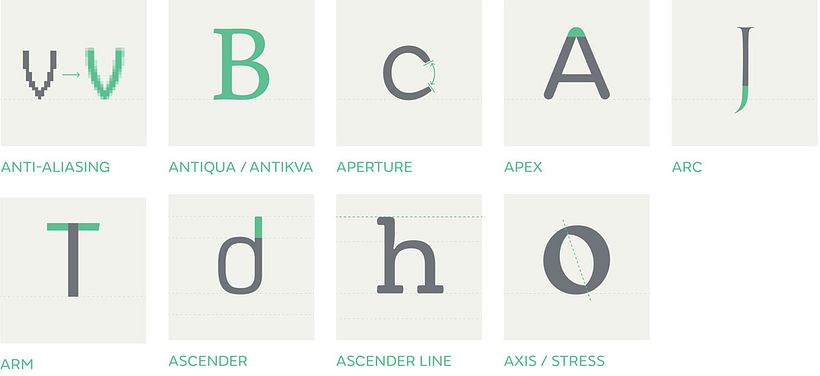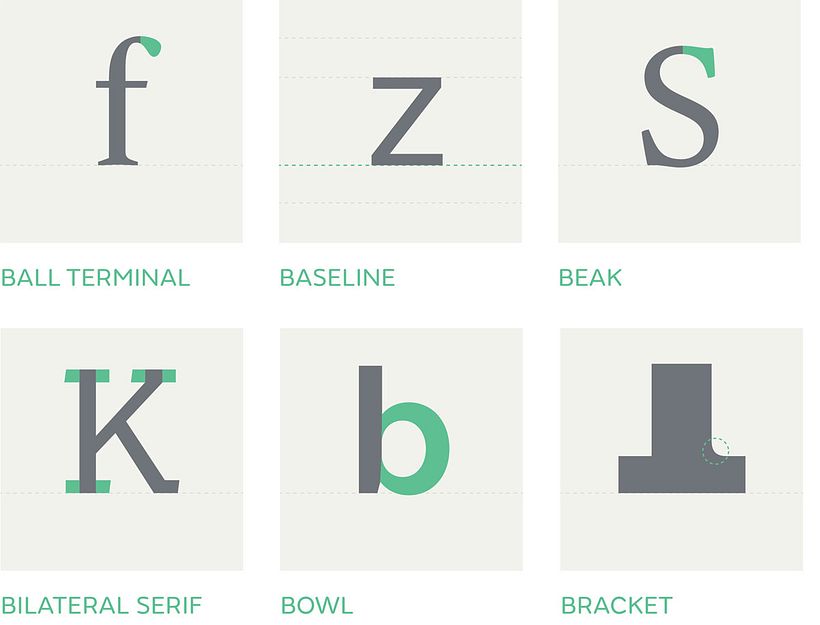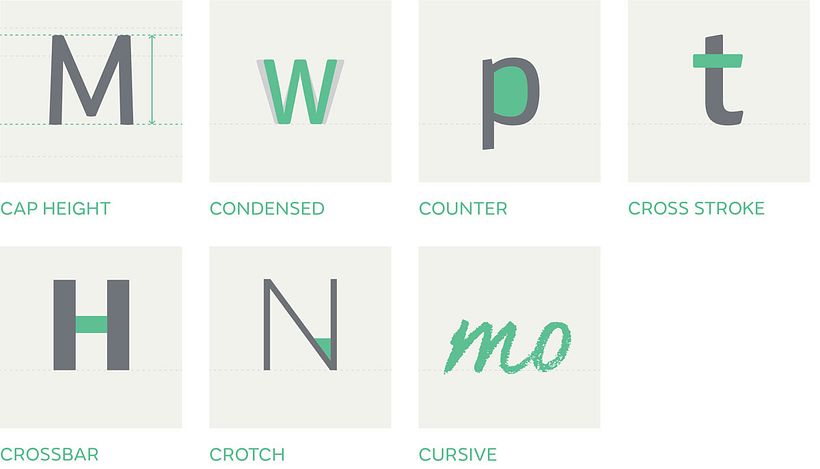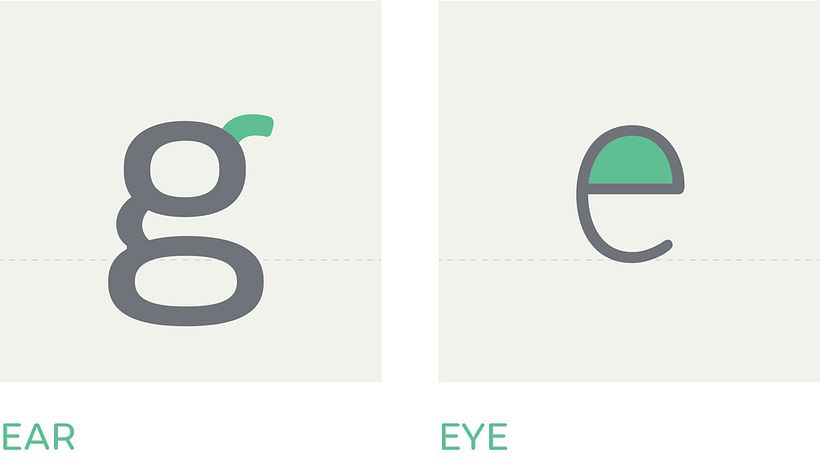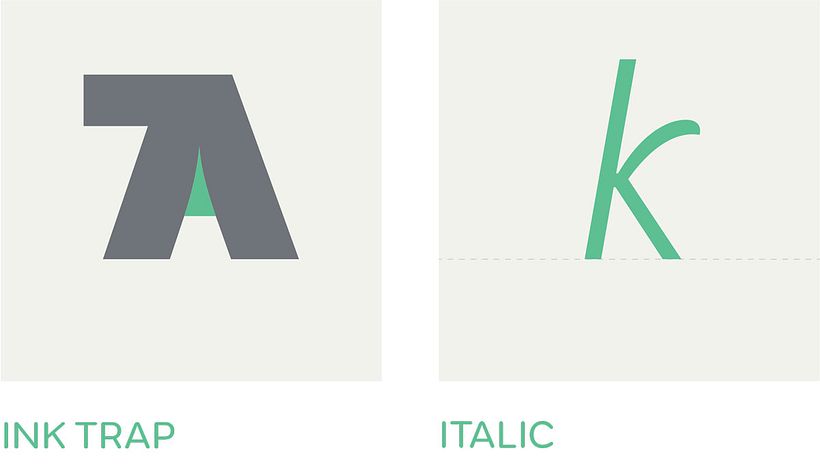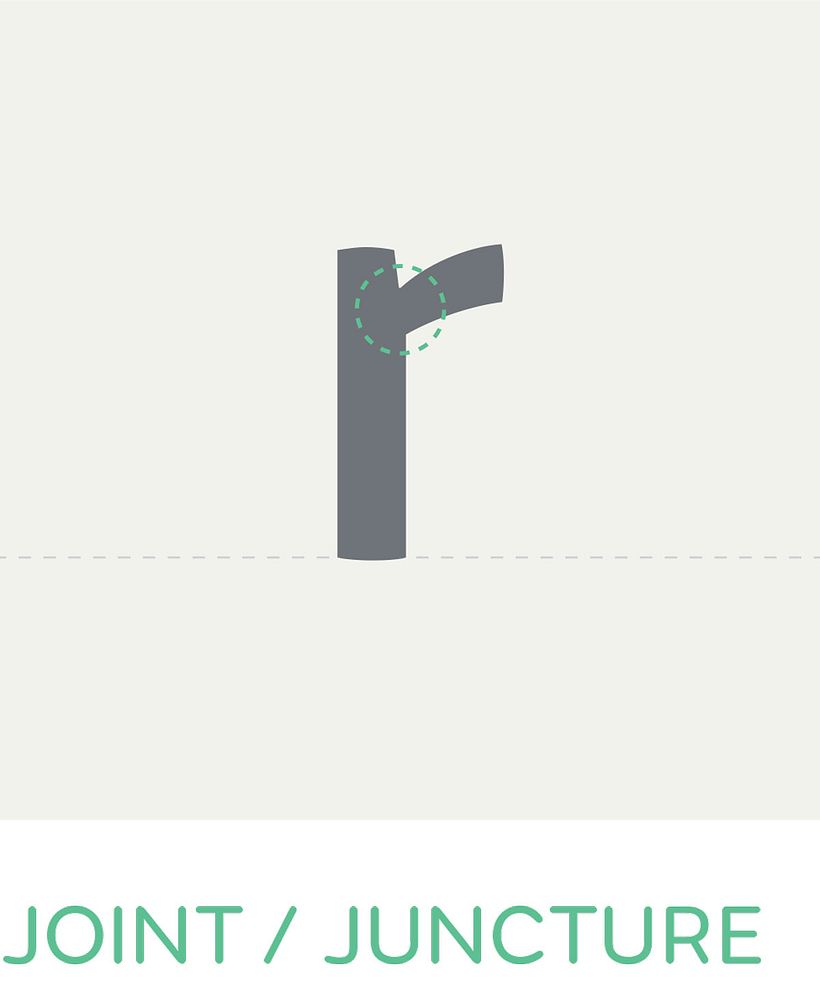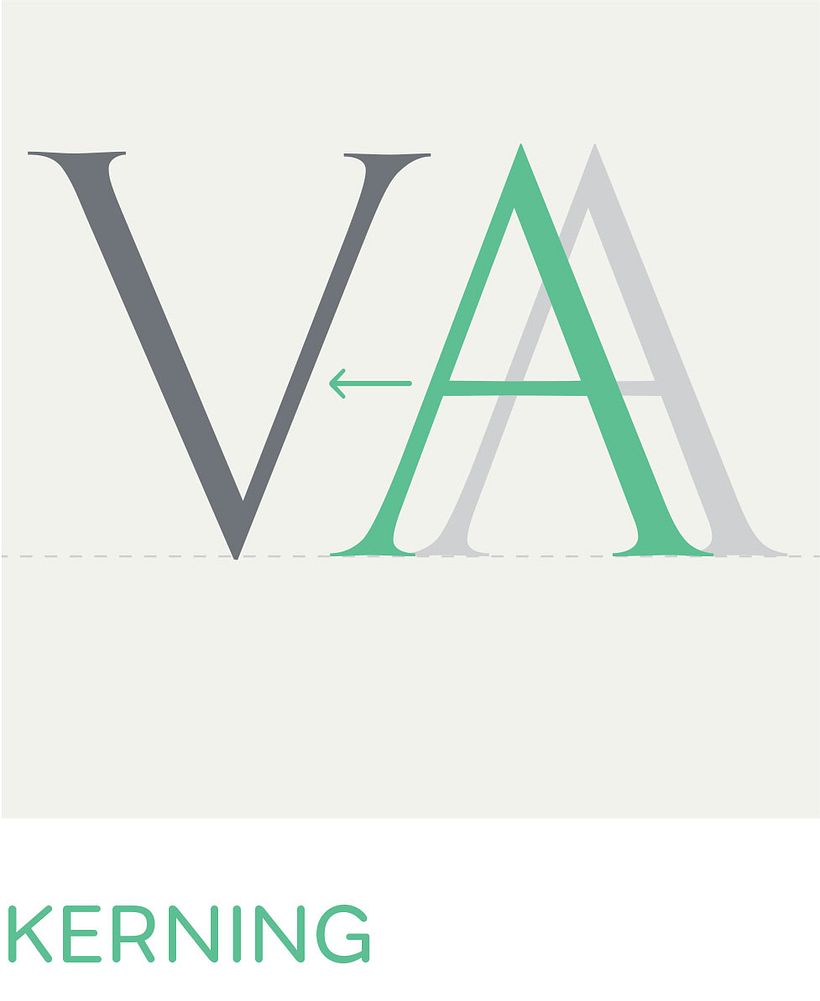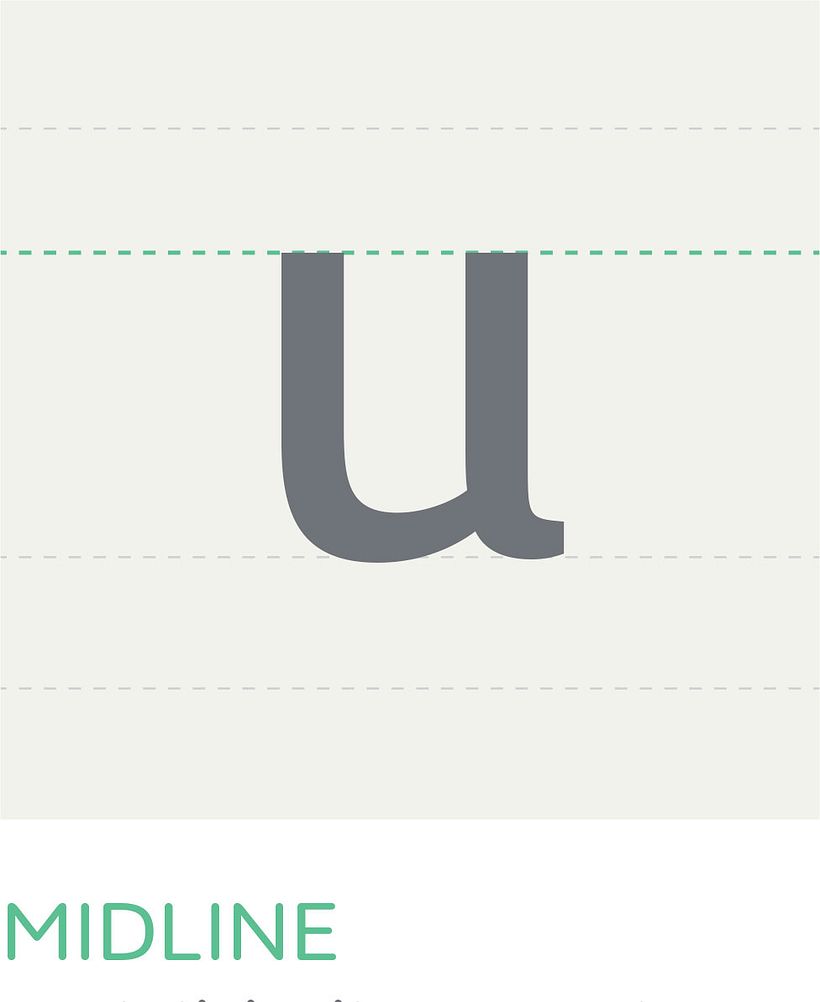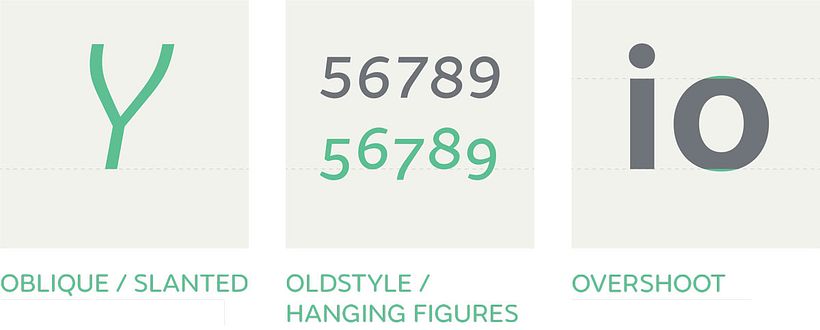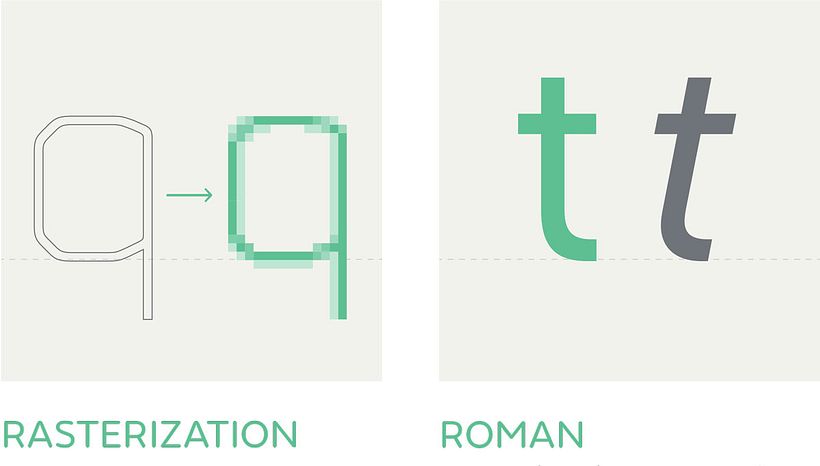
El ABC de la tipografía
El mundo de la tipografía está lleno de términos y palabras que, a menudo, pueden resultar confusos para los diseñadores.
Muchas veces no sabemos cómo referirnos a ciertas partes de la tipografía y terminamos inventando una nueva terminología.Para solventar todas estas dudas, la fundación tipográfica Fontsmith ha creado un glosario de términos tipográficos que contiene todas las expresiones relacionadas con la tipografía de la A a la Z. En ocasiones anteriores ya habíamos abordado la terminología tipográfica, pero el glosario de Fontsmith nos ha llamado la atención por lo completo y exhaustivo de su contenido.
El diccionario de términos, diseñado en formato póster, incluye representaciones gráficas y una descripción de cada uno de los términos. Originariamente se hizo en español, nosotros lo hemos traducido para aportar nuestro granito de arena al noble arte de la creación de fuentes:
A
Antialiasing. Son los píxeles semitransparentes que se agregan al glifo para evitar el efecto dientes de sierra.
Antiqua. Aquellas tipografías diseñadas en los siglos XVI y XVII, o siguiendo el estilo de estas.
Aperture (abertura). Distancia entre uno y otro segmento de una figura abierta.
Apex (ápice). Ángulo superior en el que confluyen dos trazos de una letra.
Arc (arco u hombro). Trazo curvo que sale del asta principal de algunas letras.
Arm (brazo). Trazo que no está conectado al asta principal por, al menos, uno de sus extremos.
Ascender (asta ascendente). Asta vertical que sobresale por encima de la altura de la x en las letras minúsculas.
Ascender line (línea de asta ascendiente). Línea imaginaria que marca la altura límite de las astas ascendientes de una tipografía.
Axis/stress (tensíon). Línea imaginaria que disecciona el glifo de arriba a abajo por sus extremos más estrechos.
B
Ball terminal (gota, lágrima o botón). Final de un trazo en forma redondeada.
Baseline (línea de base). Línea imaginaria que marca el punto donde se apoyan las letras sin trazos descendentes.
Break (floritura). Trazo agregado a la letra, como una serifa, pero más pronunciada, que se utiliza como adorno o como elemento de unión entre letras.
Bilateral serif (serifa bilateral). Serifa que se extiende a los dos lados del asta principal.
Bowl (bucle o panza). Trazo curvo que cierra una contraforma.
Bracket (espolón). Extensión curva que une el asta principal con la serifa.
C
Cap height (altura de las mayúsculas). Altura de la caja alta desde la línea de base.
Condensed (condensada). Tipografía cuyas proporciones han sido alteradas por el tipógrafo de manera armoniosa para que tenga un aspecto más estrecho para solucionar problemas de espacio y peso.
Counter (ojo, blanco interno o hueco). Es la forma contenida en el interior del contorno de un trazo.
Cross stroke (transversal, cruz o travesaño). Trazo horizontal que el asta vertical principal por algún punto.
Crossbar (perfil, filete o barra). Trazo horizontal entre verticales, diagonales o curvas, como ocurre en la H, la A y la E.
Crotch (vértice). Punto exterior en el que se encuentran dos trazos en la parte inferior de la letra.
Cursive (cursiva). Inclinación de la topografía con respecto a su eje que intenta imitar los rasgos caligráficos.
D
Descender (descendente). Parte de los caracteres de caja baja que se extiende por debajo de la línea de base.
Descender line (línea descendente). Línea imaginaria que marca el punto hasta el que se extienden las descendentes.
Display font (tipografía display). Son aquellas que han sido pensadas para ser utilizadas en cuerpos grandes como banners o titulares.
E
Ear (oreja o lóbulo). Pequeño trazo terminal de algunos caracteres como la g de caja baja.
Eye (ojo, blanco interno o hueco). Igual que 'counter', es la forma interior contenida dentro de un trazo.
F
Finial (remate). Terminación curva o afilada de algunas letras como la e o la c.
Flag. Trazo horizontal característico del número 5.
Foot (serifa, gracia, patín o pie). Trazo terminal ornamentar de un asta, brazo o cola. No es indispensable y es herencia de la escritura con pluma cuadrada.
G
Gadzook (ligadura). Trazo que une dos o varios grafemas de modo ornamental que no forma parte de ninguno de los glifos.
Glyph (glifo). Representación gráfica de un carácter. 'A' y 'a' son diferentes glifos de un mismo carácter.
Grotesk (grotescas). Es el nombre aleman para las tipografías sin serifa.
H
Hairline. El trazo más fino de una letra.
Halbfett. Nombre aleman para el estilo semi-bold de una tipografía.
Head serif. Serifa situada en el extremo superior de un glifo.